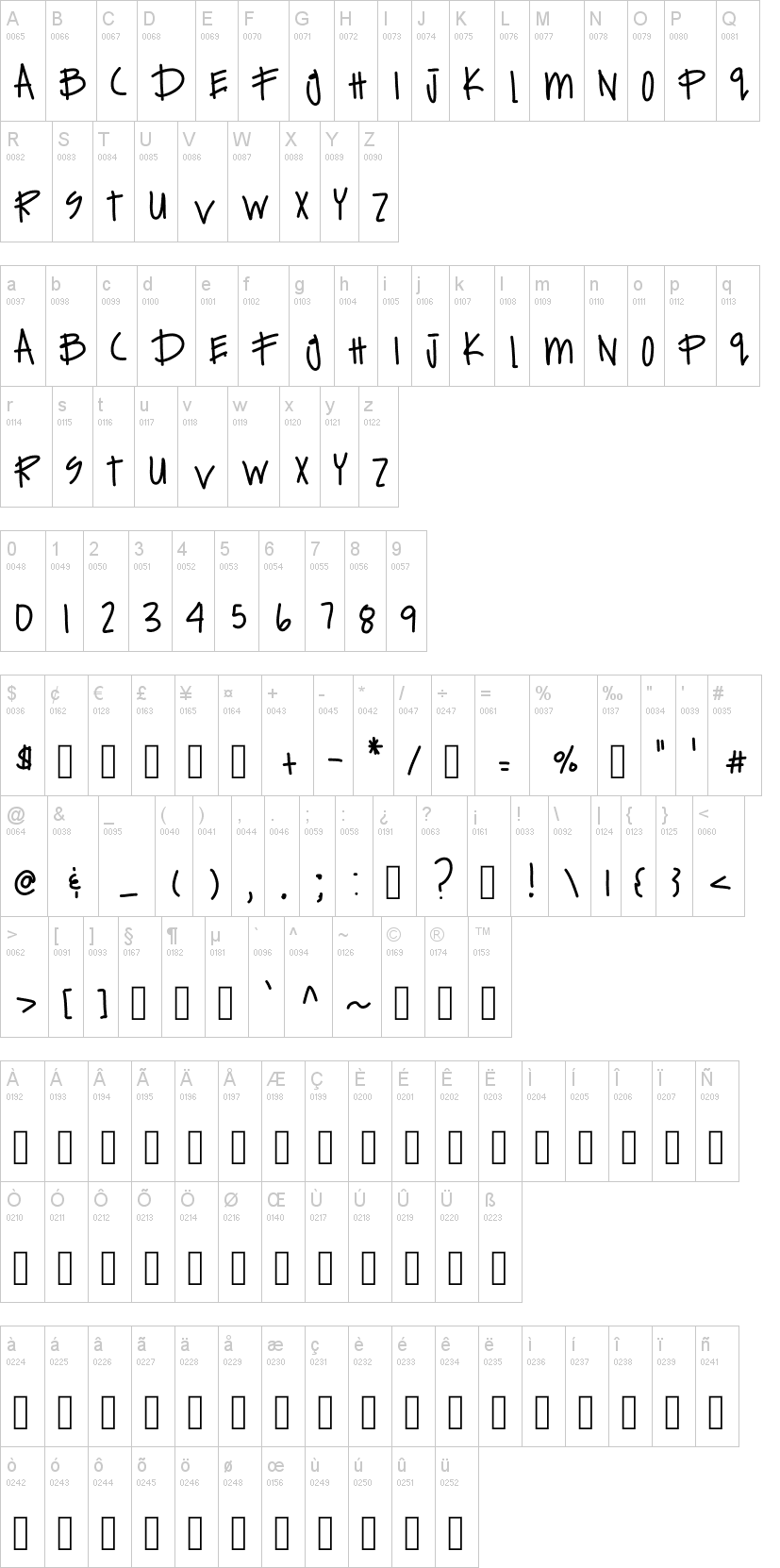
Expensive Habits
Expensive Habits 是一款比较有特色的字体,它的特点是有着清晰的轮廓和复杂的细节。它的字体有着柔和的曲线,具有极强的视觉冲击力。它的字体风格也比较复古,有着独特的复古风格,可以用于设计师的各种设计作品中。
Expensive Habits是一款非常不错的手写艺术字体,具有很好的视觉感,适合于文化类的宣传设计、商业类品牌的广告和产品包装设计以及个性化文字排版等较多场景。